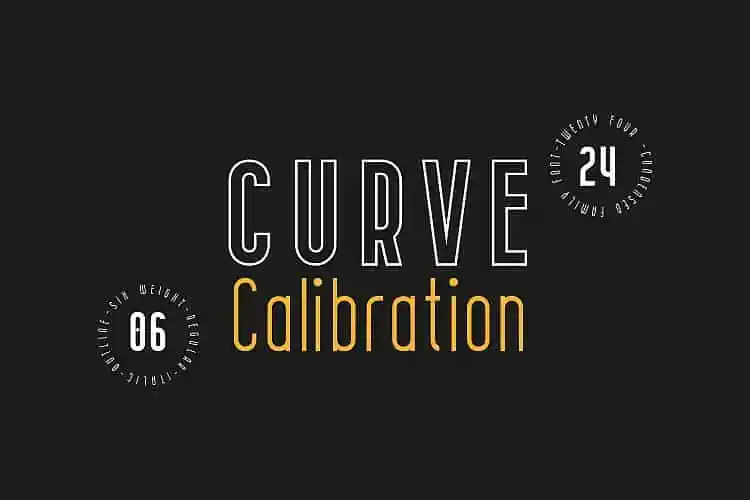
CURVE Calibration Typeface – Download Grátis
A Fonte CURVE Calibration é uma tipografia sans-serif minimalista que traz beleza para qualquer contexto. Introduzimos a CURVE Calibration, uma família universal de serifas. Ela possui um estilo simples nos traços, um espaço de abertura fechado e formas geométricas. Esta fonte vem em 24 variações perfeitas para arrays extensos de texto. A design individualmente desenvolvido dos cada gírifo permite que você utilize-a com sucesso como uma fonte de exibição. Esta tipografia é ideal tanto para uso cotidiano quanto para aplicações visuais exigentes, tornando-se um recurso indispensável em qualquer projeto gráfico. Engajante e versátil, a CURVE Calibration Font de 24Design é uma escolha inteligente para designers que valorizam simplicidade e elegância moderna em suas criações.